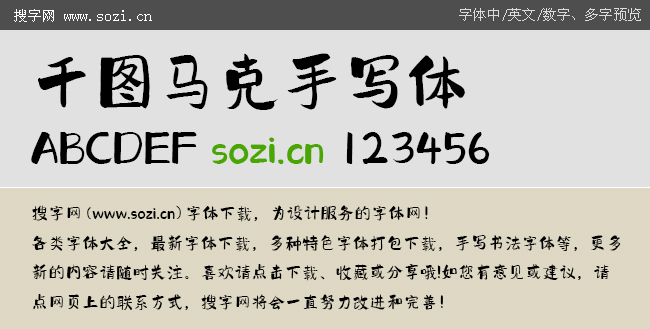
千圖馬克手寫體
搜字網(wǎng)給大家提供一款千圖馬克手寫體(非商業(yè)使用)中文字體下載,該字體是一款手寫風(fēng)格的藝術(shù)字體,筆畫開張有度,字面留有充足空間,字間保持合適的距離,讓排列變得通透,閱讀更加輕松、舒服,有如自在呼吸。既適合做標(biāo)題又適合做提醒類的文字,適用于各類場(chǎng)景。